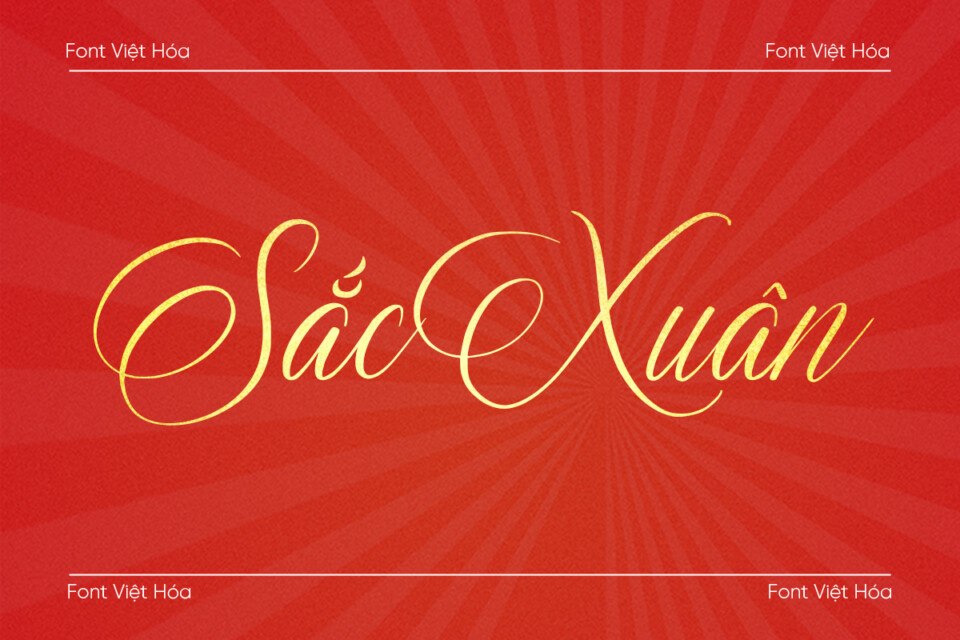
Font Việt hóa 1FTV VIP Westwood Studio – Font tết
Giới thiệu bộ Font Việt hóa 1FTV VIP Westwood Studio – Font tết
Trong thế giới thiết kế đồ họa hiện đại, việc tìm kiếm một bộ Font Miễn Phí chất lượng cao và phù hợp với văn hóa Việt Nam luôn là ưu tiên hàng đầu của các nhà sáng tạo. Đặc biệt, khi không khí mùa xuân đang đến gần, bộ Font Việt hóa 1FTV VIP Westwood Studio – Font tết nổi lên như một lựa chọn hoàn hảo để truyền tải thông điệp may mắn và hạnh phúc. Đây là một bộ phông chữ được tinh chỉnh kỹ lưỡng, giữ trọn nét cổ điển của phong cách Westwood Studio nhưng vẫn mang đậm hơi thở lễ hội truyền thống của người Việt. Việc sử dụng bộ phông này giúp các ấn phẩm thiết kế trở nên nổi bật, sang trọng và đầy tính chuyên nghiệp trong mắt người xem.
Đặc điểm nổi bật của Font Việt hóa 1FTV VIP Westwood Studio – Font tết
Phong cách thiết kế độc đáo và linh hoạt
Bộ Font Việt hóa 1FTV VIP Westwood Studio – Font tết sở hữu những đường nét mạnh mẽ, dứt khoát nhưng không kém phần mềm mại ở các góc cạnh. Điều này giúp phông chữ phù hợp với nhiều loại dự án khác nhau từ banner quảng cáo, thiệp chúc mừng năm mới đến các ấn phẩm truyền thông học đường. Với cấu trúc ký tự đặc biệt, phông chữ này giúp các nhà thiết kế dễ dàng tạo điểm nhấn cho tiêu đề bài viết hoặc các câu đối Tết ý nghĩa. Sự kết hợp giữa nét chữ phương Tây và tâm hồn Việt đã tạo nên một tác phẩm nghệ thuật chữ viết ấn tượng, giúp tăng khả năng nhận diện thương hiệu và thu hút sự chú ý của cộng đồng.
Tối ưu hóa tiếng Việt và khả năng hiển thị
Một trong những ưu điểm lớn nhất của Font Việt hóa 1FTV VIP Westwood Studio – Font tết chính là việc xử lý dấu tiếng Việt cực kỳ mượt mà. Thông thường, các phông chữ quốc tế khi sử dụng dấu thường bị lỗi hiển thị hoặc khoảng cách không đều, nhưng phiên bản 1FTV VIP này đã khắc phục hoàn toàn các nhược điểm đó. Các dấu thanh như huyền, sắc, hỏi, ngã, nặng được đặt vị trí chuẩn xác, giúp văn bản trở nên dễ đọc và thẩm mỹ hơn. Ngoài ra, phông chữ còn tương thích tốt trên cả hai hệ điều hành Windows và macOS, đảm bảo quá trình làm việc của bạn luôn diễn ra suôn sẻ và đạt hiệu quả cao nhất trong mọi hoàn cảnh.
Ứng dụng thực tế của Font Việt hóa 1FTV VIP Westwood Studio – Font tết
Sáng tạo nội dung cho mùa lễ hội
Vào dịp cuối năm, nhu cầu thiết kế bao lì xì, trang trí lớp học hay làm video chúc mừng tăng cao. Font Việt hóa 1FTV VIP Westwood Studio – Font tết là trợ thủ đắc lực giúp các bạn học sinh và giáo viên tạo ra những sản phẩm giáo dục mang tính thẩm mỹ cao. Bạn có thể sử dụng phông chữ này để viết các lời chúc hay, thiết kế bảng tin nhà trường hoặc làm các poster sự kiện hội xuân. Sự trang trọng và ấm cúng mà bộ chữ này mang lại sẽ góp phần làm cho không gian Tết thêm phần ý nghĩa và rực rỡ, giúp thắt chặt tình cảm thầy trò và bạn bè thông qua những nét chữ tinh tế.
Kết luận về bộ Font Việt hóa 1FTV VIP Westwood Studio – Font tết
Tổng kết lại, đây là một bộ phông chữ không thể thiếu trong kho tài nguyên của bất kỳ ai yêu thích cái đẹp và sự chỉn chu. Việc lựa chọn đúng phông chữ không chỉ giúp sản phẩm của bạn chuyên nghiệp hơn mà còn thể hiện được sự tôn trọng đối với người xem. Nếu bạn đang tìm kiếm một công cụ hỗ trợ thiết kế đắc lực, đừng ngần ngại tải về và trải nghiệm Font Miễn Phí, Font Việt Hóa, Font Việt hóa 1FTV VIP Westwood Studio – Font tết ngay hôm nay. Hãy để sự sáng tạo của bạn bay xa cùng với những nét chữ tuyệt đẹp này, biến mọi ý tưởng thành hiện thực và mang không khí Tết tràn ngập vào trong từng tác phẩm của mình nhé!